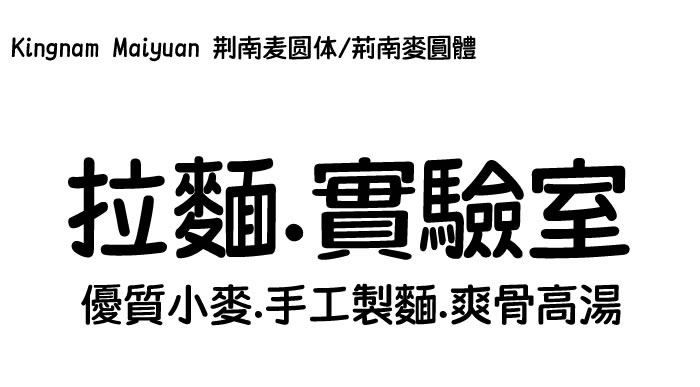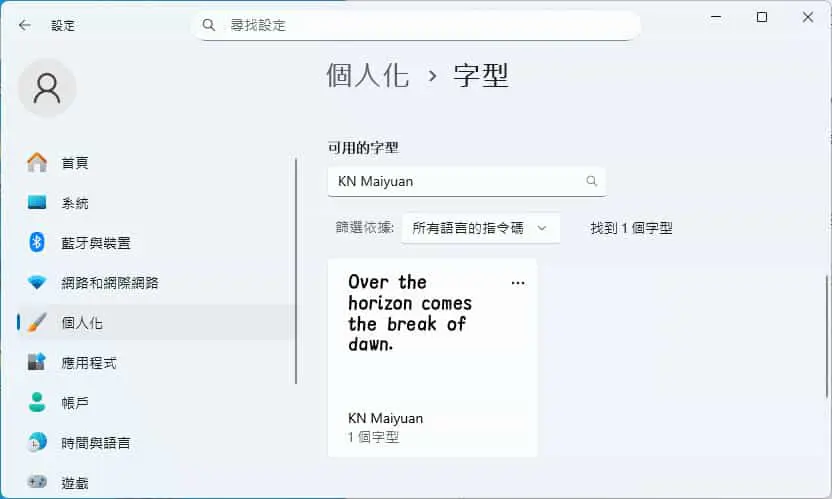
在尋找一款既可愛又專業的中文字體嗎?今天要介紹的「荊南麥圓體」(KN Maiyuan)絕對值得你收藏!這款由荊南字坊(Kingnam Type Foundry)推出的手寫字體,不僅風格獨特,更重要的是完全免費商用,無論是個人創作還是商業設計都能安心使用。
字體特色
萌系可愛的手寫風格
荊南麥圓體的設計靈感來源於韓國綜藝節目上的韓文字體,將那種圓潤可愛的風格完美融入中文字體設計中。整體呈現出溫暖親切的手寫感,卻又保持了良好的可讀性。
設計亮點
- 圓潤飽滿的筆畫:每個筆畫的粗細相同,兩端圓潤飽滿,展現可愛風格
- 橫畫略帶傾斜:模擬真實手寫的自然感
- 日字不封口:更接近手寫特徵,增添趣味性
- 筆畫分明清晰:雖是手寫字體,但沒有細小的連接,保持清新俏皮的視覺效果
- 螢幕顯示友善:在保留趣味性的同時,具備高可讀性,適合各種媒介使用
字數涵蓋範圍
荊南麥圓體的字數非常完整,總共收錄了 13,375 個漢字,涵蓋範圍相當於方正簡繁字庫加上日文 Pro 標準收錄的所有漢字,並額外補充了部分香港增補字符集的漢字。
結語
荊南麥圓體是一款非常優秀的免費中文字體,它成功地將可愛與實用性結合在一起。無論你是平面設計師、UI 設計師,還是經營社群媒體的小編,這款字體都能為你的作品增添溫暖親切的氛圍。